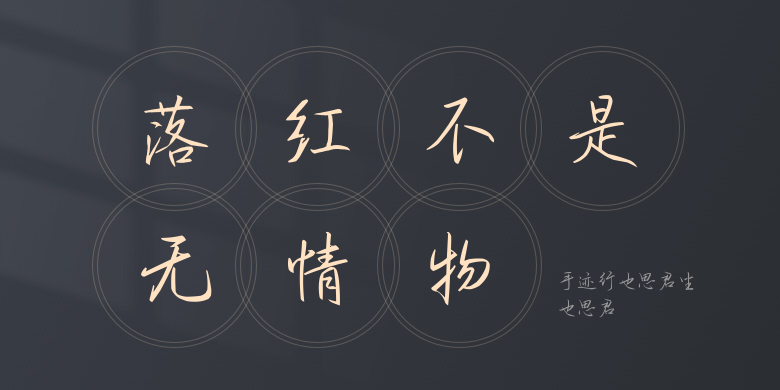
手迹行也思君坐也思君
手迹行也思君坐也思君,这款字体结构工整、笔画清晰,兼顾美观与易读性,适用于标题、正文、海报、包装、LOGO 等多种场景。字形优雅稳定,风格百搭耐看,适配日常排版与创意设计,让文字呈现更舒适、更具质感。手迹行也思君坐也思君一笔一画,皆是细节,以均衡的比例、流畅的线条打造舒适视觉体验,字形端正大气,风格简约现代。无论是商业设计、品牌宣传还是日常排版,都能轻松驾驭,让文字更有格调与力量。手迹行也思君坐也思君字体下载。